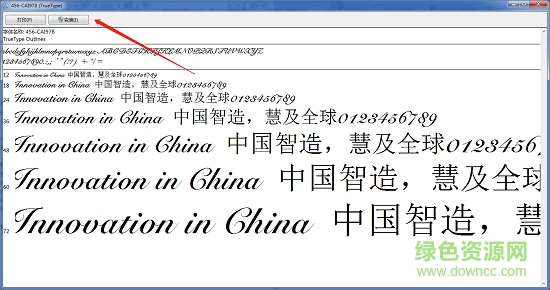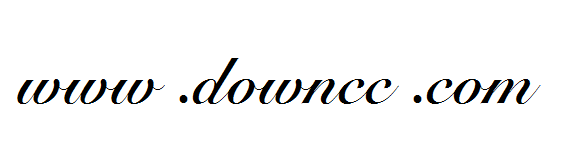
456-cai978
456-cai978字體ttf版是一款風格非常的飄逸的英文字體,看起來非常的舒適,適用于各類因為排版以及其他的設計主體,整齊規(guī)劃非常的完美,喜歡的用戶快來綠色資源網(wǎng)下載吧!
456-cai978字體簡介:
456-cai978字體是一款非常簡約的花式英文字體。使用這款字體敲打出來的內(nèi)容很整齊,視覺效果也很好,而且它支持英文、數(shù)字以及英文狀態(tài)下的標點符號,喜歡這種類型字體的用戶可以直接在本站免費下載!